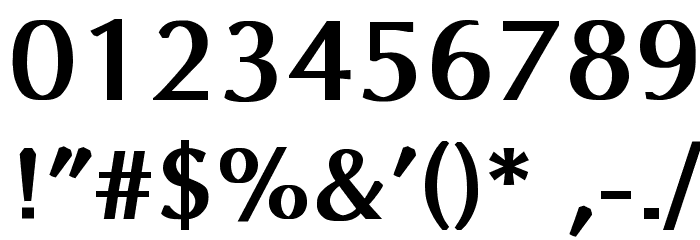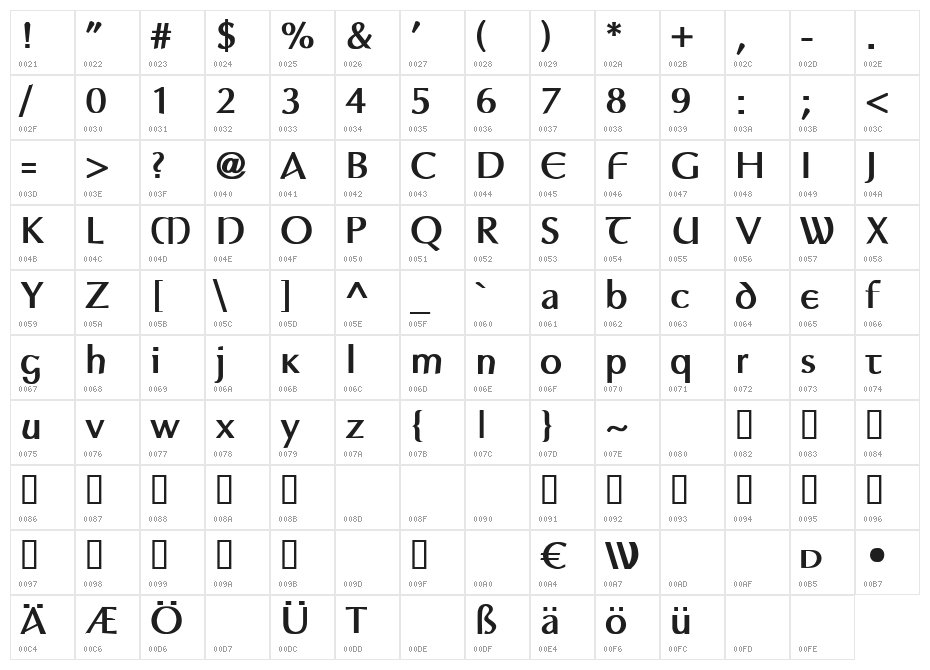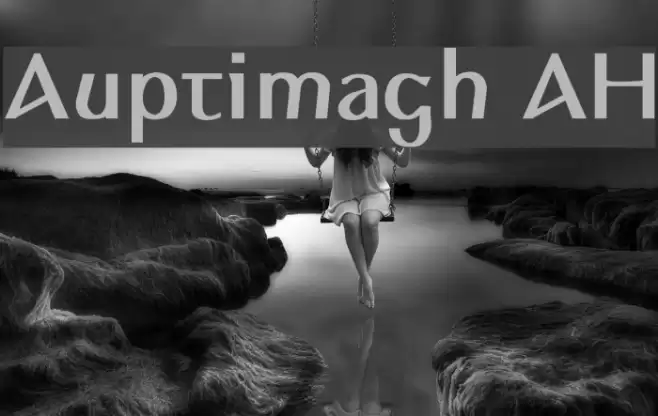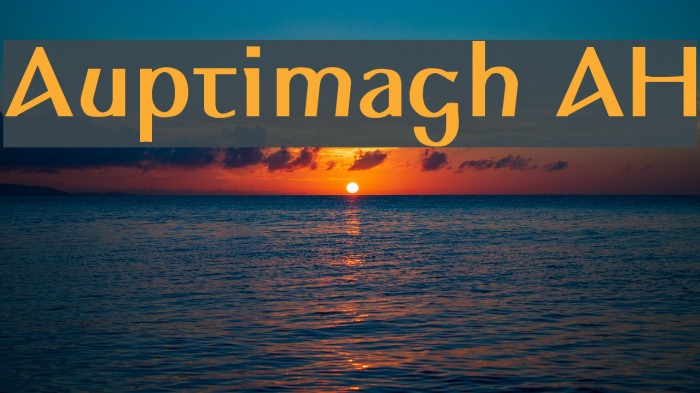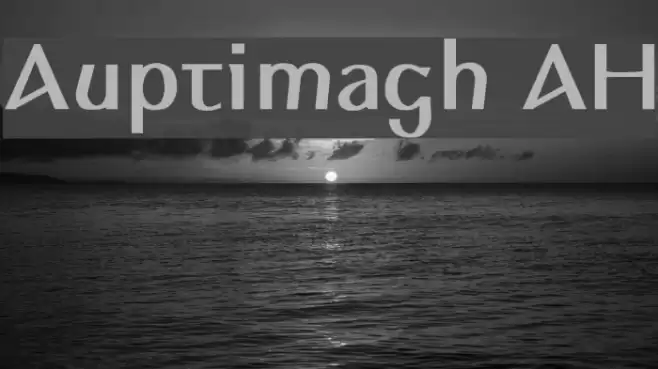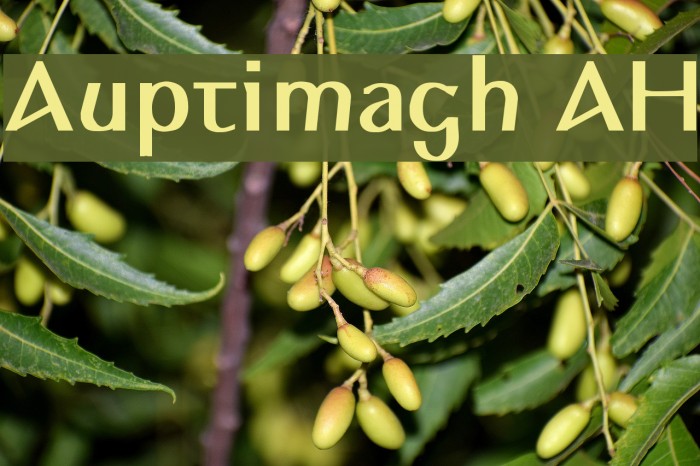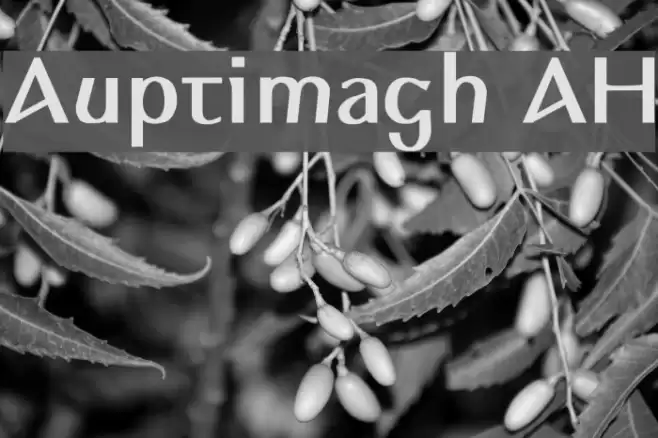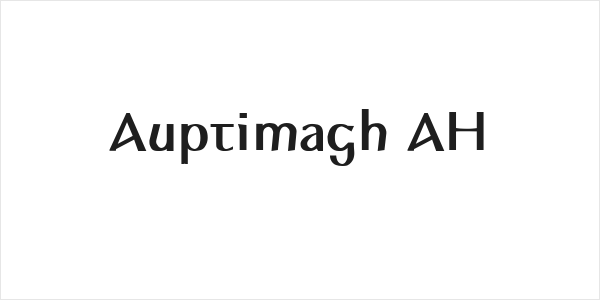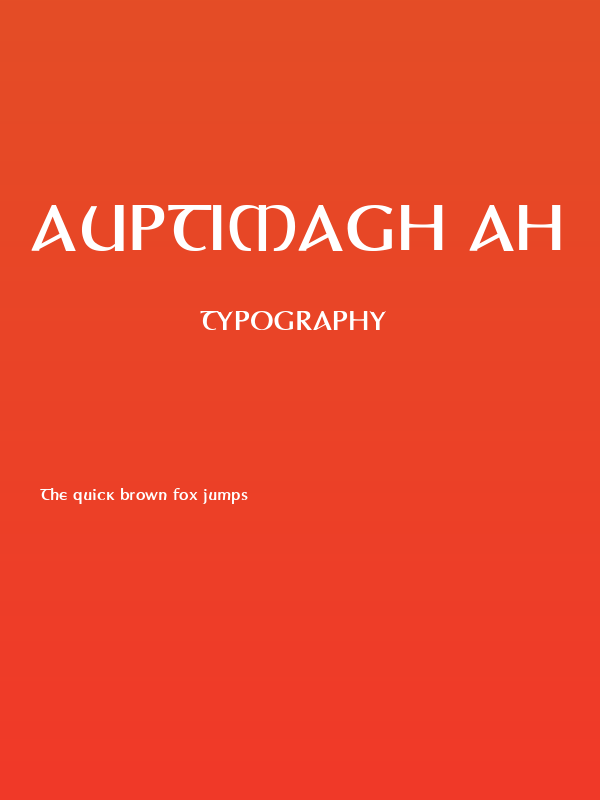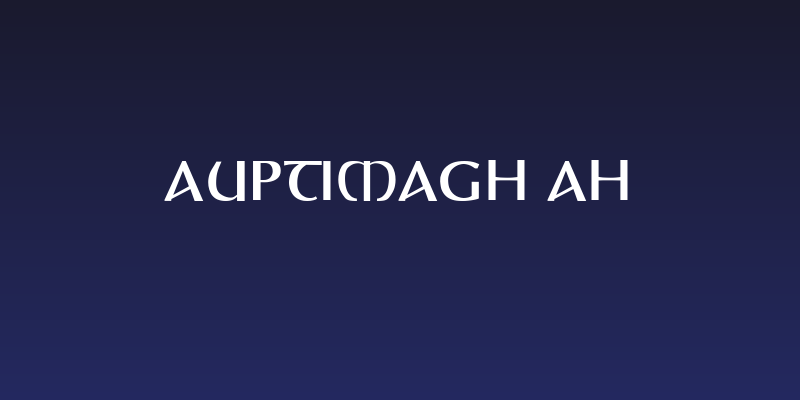
Auptimagh AH Font
| Cas d'utilisation | Headlines, Logos, Editorial design |
| Projets proposés | This font is perfect for branding, editorial design, advertising, and digital media projects that require a modern and sophisticated touch. |